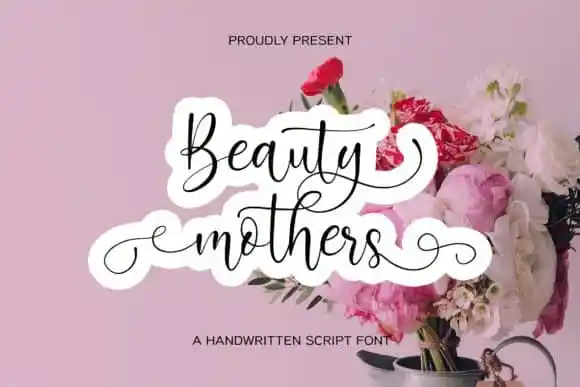
Beauty Mothers Script Font – Download Grátis
Introduzimos Beauty Mothers Script Font, uma nova fonte de estilo Calligrafiado! Ideal para quem busca um toque de elegância e modernidade nos seus projetos, esta criação foi feita especialmente para você. Com a sua forma redonda, é simplesmente perfeito para adicionar um toque decorativo em segundos. JunCreative concebeu este encantador recurso gráfico. Beauty Mothers promete inspirá-lo constantemente, ajudando-o a criar designs impactantes, convites de casamento, cartões de aniversário, cartas de cumprimento e muito mais. Sinta-se à vontade para explorar a beleza deste novo recurso fonte!